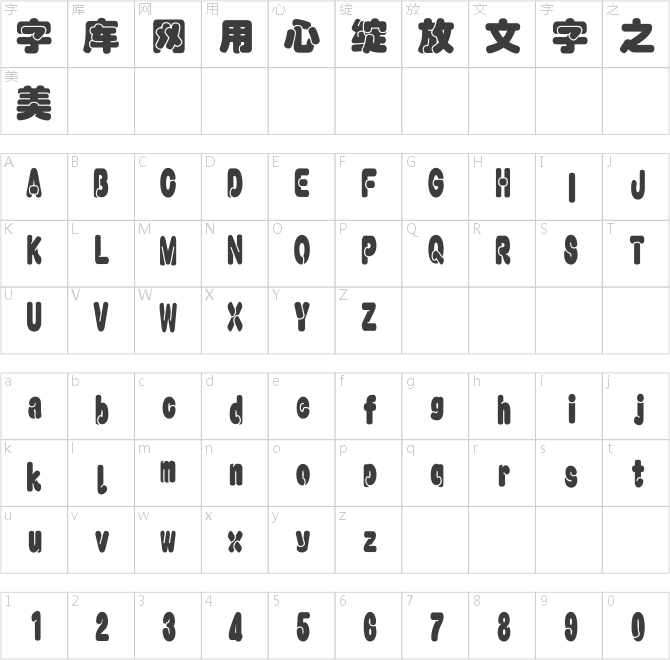
?文鼎琥珀簡(jiǎn)繁
文鼎字庫(kù)
文鼎琥珀的簡(jiǎn)體和繁體big5合并形成的,二次修訂時(shí)補(bǔ)全了原big5的漢字,兼容新版win10
更新Power TrueType Version 5.0版,和原Power TrueType Version 4.0或Power TrueType Version 4.5版本相比又將原Power TrueType big5的擴(kuò)展471個(gè)外字集的部分沒有映射字碼點(diǎn)的漢字進(jìn)行了對(duì)號(hào)入座,并修復(fù)『?』字誤映射到『抝』字位置的錯(cuò)誤。
20220120更新Power TrueType Version 5.5版:添加日語(yǔ)當(dāng)用漢字。一共16721個(gè)漢字。
20220204更新:修正「爲(wèi)」「僞」分別顯示為「為」「?jìng)巍沟腻e(cuò)誤。
?文鼎琥珀簡(jiǎn)繁字體?文鼎疊圓簡(jiǎn)繁字庫(kù)是一款讓人賞心悅目、百看不厭的中文字體,適合各類廣告和產(chǎn)品包裝設(shè)計(jì)應(yīng)用,字體大小14.27MB,格式為ttf字體,上傳用戶是伊寧,作者/版權(quán)方為文鼎字庫(kù)